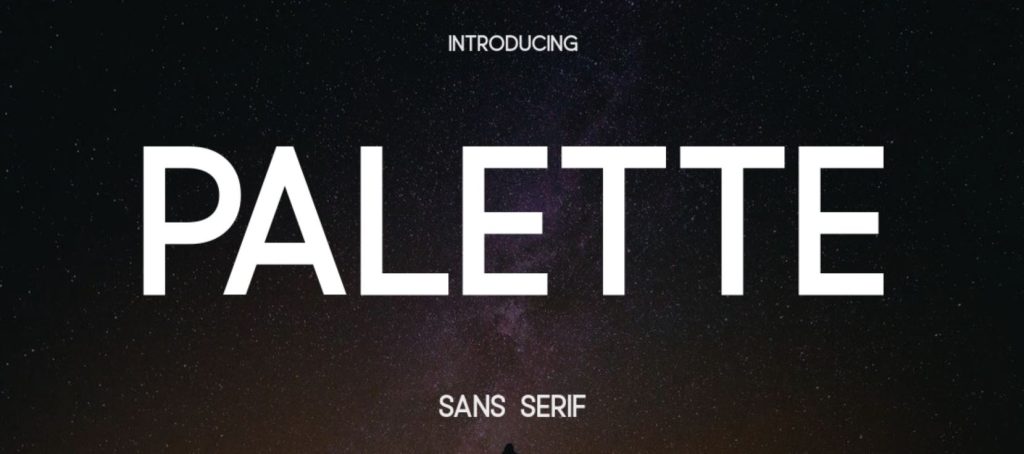
Palette Font
Bộ Font: Font Palette
Phân loại: Đa dạng màu sắc
Font Palette thuộc bộ font chữ trang trí công cụ hoàn hảo cho những nhà thiết kế muốn tạo ra các tác phẩm đa dạng và phong phú về mặt chữ. Với sự kết hợp của nhiều kiểu chữ độc đáo trong một bộ sưu tập, Font Palette giúp bạn dễ dàng lựa chọn và pha trộn các phông chữ để tạo nên những thiết kế sáng tạo và ấn tượng. Dù bạn đang làm việc với logo, tiêu đề hay ấn phẩm quảng cáo, Font Palette cung cấp sự linh hoạt để đáp ứng mọi nhu cầu thiết kế. Khám phá ngay Font Palette để biến ý tưởng thành hiện thực với những kiểu chữ đa dạng và bắt mắt.